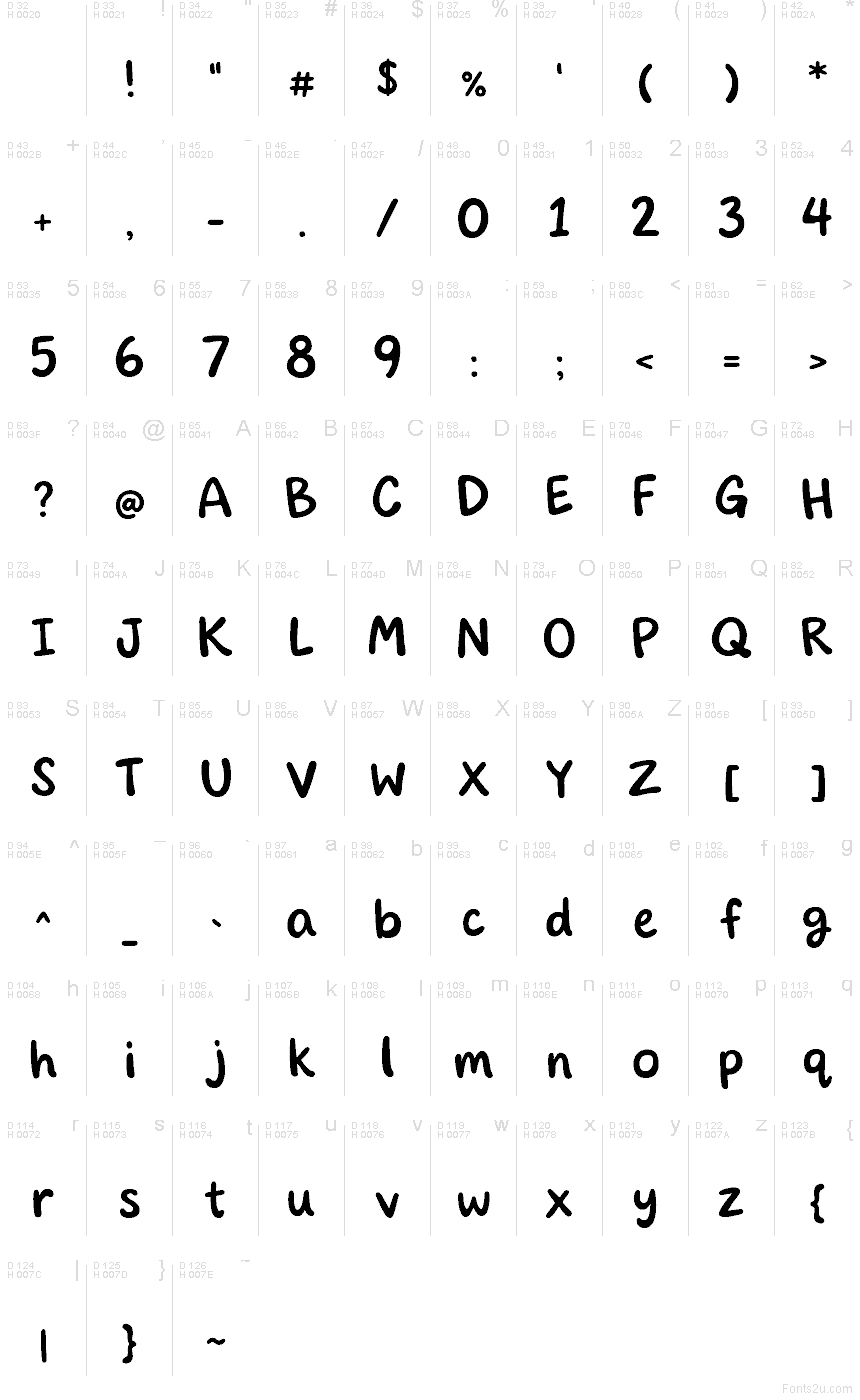
Sweet Cucumber Mocktail es una tipografía manuscrita gratuita de Misti's Fonts, inspirada en el ritmo relajado de las letras hechas con pincel. Sus trazos redondeados y formas sutilmente irregulares transmiten una sensación cálida y espontánea, mientras que sus bucles generosos hacen que la escritura se sienta abierta y cercana.
Utiliza esta fuente gratuita para menús de cafeterías, etiquetas de bebidas, tarjetas de recetas, letreros de tiendas y publicaciones alegres en redes sociales. Funciona especialmente bien en titulares cortos, donde sus uniones relajadas y curvas dinámicas pueden llevar el diseño por sí mismas sin necesidad de adornos extra.